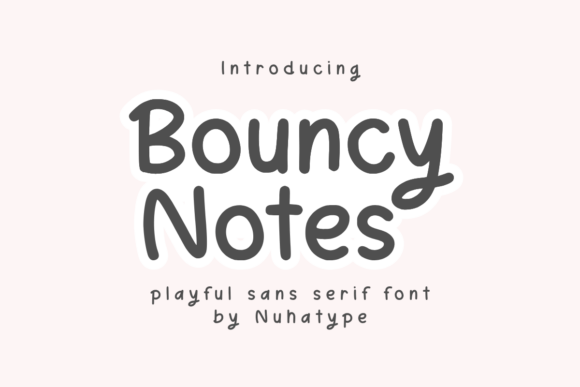
Bouncy Notes
適切なデザイン要素を見つけるのは難しい場合がありますが、Bouncy Notesは作品を即座に引き立てる優れたコレクションを提供します。
POD(オンデマンド印刷)製品、結婚式の招待状、またはソーシャルメディアのグラフィックを作成している場合でも、Bouncy Notesは理想的です。